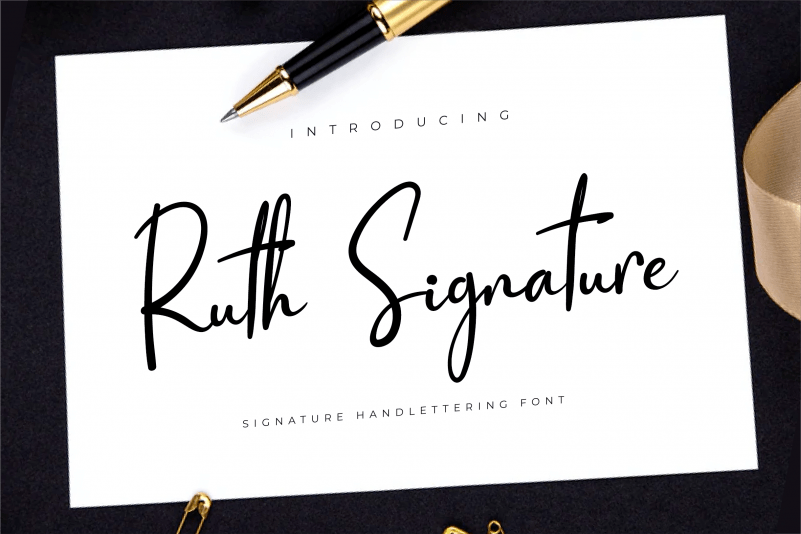
Ruth Signature Font – Download Grátis
A Ruth Signature Font é uma elegante fonte escrita a mão com traços suaves que se tornam grossos conforme avançamos pelo texto. Ela é perfeita para quem busca uma combinação entre simplicidade e robustez, ideal para estilos de marca e embalagens que precisam de um toque único e imediato. Esta fonte foi cuidadosamente projetada, tornando-se um elemento indispensável tanto para logos quanto para trabalhos de identificação visual e embalagem. Seja na criação de logotipos, em design de marca ou até mesmo nas embalagens de produtos, Ruth Signature será uma escolha inteligente que fará seu trabalho perfeitamente, oferecendo um toque personalizado e sofisticado.